싸인은 단순한 서명이 아니라 자신을 표현하는 중요한 요소예요. 특히, 자신의 이름을 활용한 싸인은 더욱 신뢰감을 주고, 공식 문서에서도 활용 가능하죠. 🖋️✨
하지만 단순히 이름을 쓰는 것만으로는 멋진 싸인을 만들기 어렵기 때문에, 고려해야 할 몇 가지 요소를 체크하는 것이 중요해요. 먼저, 이름 기반 싸인의 중요성부터 알아볼까요? 🔍
이름 기반 싸인의 중요성 🖊️
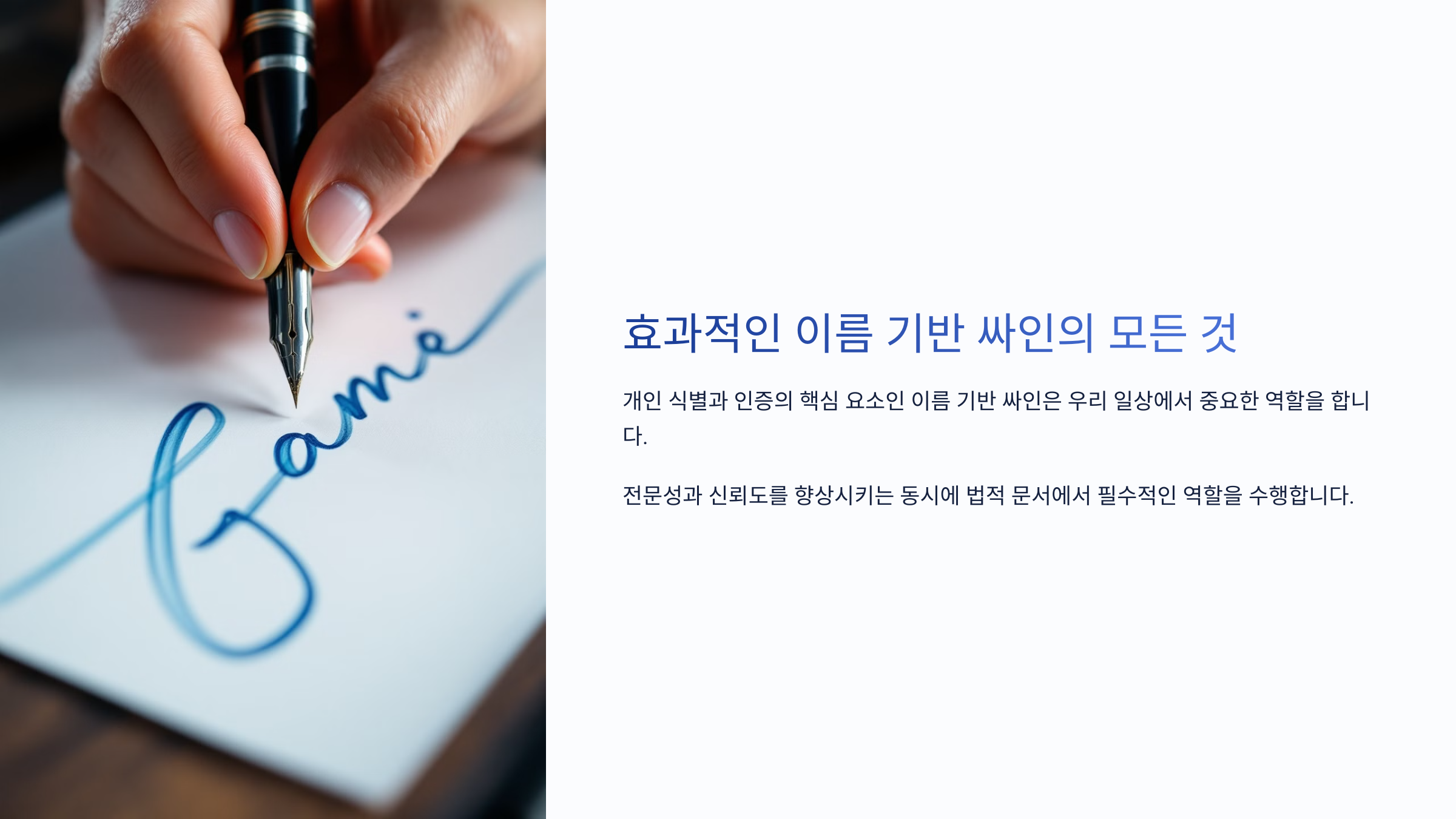
자신의 이름을 활용한 싸인은 가장 기본적이면서도 신뢰감을 주는 스타일이에요. 특히 공식 문서, 계약서, 신용 거래 등에서 본인 확인의 역할을 하기 때문에 더욱 중요하죠. ✅
싸인은 단순한 글씨가 아니라 자신의 브랜드이자 아이덴티티예요. 빌 게이츠, 스티브 잡스, 제프 베이조스처럼 이름을 활용한 싸인을 보면 그들의 개성과 스타일이 명확하게 드러나요.
📌 이름 기반 싸인이 중요한 이유 ✅
이유 설명 공식 문서에서의 신뢰감 이름 기반 싸인은 계약서, 법적 서류에서 본인 확인 수단이 됨 개인 브랜드 강화 고유한 싸인은 나만의 브랜드 이미지와 연결될 수 있음 가독성과 실용성 이름을 기반으로 하면 쉽게 읽히면서도 깔끔한 인상을 줌 위조 방지 효과 독특한 스타일을 더하면 위조가 어려워 보안성이 높아짐 이름을 기반으로 한 싸인은 가독성과 신뢰성을 동시에 확보할 수 있는 강력한 방법이에요. 하지만, 너무 단순하면 흔해 보일 수 있고, 너무 복잡하면 가독성이 떨어질 수 있어요. 그럼 이제, 가독성과 스타일을 적절히 조합하는 방법을 알아볼까요? ✨
가독성과 스타일의 균형 ⚖️
싸인은 가독성이 좋아야 신뢰감을 줄 수 있고, 스타일이 있어야 개성이 살아나요. 하지만 이 두 가지를 동시에 만족시키는 것이 쉽지 않죠. 😵💫너무 복잡한 싸인은 빠르게 작성하기 어렵고, 공식 문서에서 문제가 될 수 있어요. 반대로 너무 단순한 싸인은 개성이 부족해 보일 수 있죠. 그래서 이름을 유지하면서도 멋진 스타일을 가미하는 균형이 중요해요! 🖊️
📌 가독성과 스타일을 조합하는 4가지 원칙 ✅
원칙 설명 1. 핵심 글자는 명확하게 이름의 첫 글자 또는 성을 명확하게 남기고 나머지는 부드럽게 처리 2. 곡선과 직선의 조화 부드러운 곡선과 강한 직선을 조합해 개성 있는 스타일 연출 3. 적절한 속도감 너무 빠르면 흐트러지고, 너무 느리면 부자연스러우니 적절한 속도로 연습 4. 서명의 일관성 싸인의 스타일을 일정하게 유지해 모든 문서에서 동일한 모습 유지 이 원칙을 적용하면 읽기 쉽고, 멋있고, 실용적인 싸인을 만들 수 있어요! 그럼 이제, 이니셜을 활용해 더 특별한 싸인을 만드는 방법을 알아볼까요? ✨
이니셜을 활용하는 방법 🔠
싸인에서 이니셜(첫 글자)을 강조하면 스타일과 개성을 살릴 수 있어요. 특히 긴 이름을 가진 경우, 이니셜을 활용하면 싸인을 짧고 세련되게 만들 수 있죠. ✍️
빌 게이츠(Bill Gates) → B. Gates 일론 머스크(Elon Musk) → E. Musk 이처럼 이니셜을 활용하면 짧으면서도 강한 인상을 주는 싸인을 만들 수 있어요! 🔥
📌 이니셜을 활용하는 4가지 방식 ✅
방식 설명 예시 1. 성 + 이니셜 성을 적고, 이름은 첫 글자만 남기는 방식 "Kim J." / "Choi S." 2. 이니셜 조합 이름과 성의 첫 글자를 합쳐 심플하게 만들기 "J.K." / "S.L." 3. 이니셜 + 서명 스타일 이니셜을 강조하고, 개성 있는 서명 요소 추가 "J.K ✨" / "S.L ↘" 4. 필기체 스타일 이니셜을 손글씨 느낌으로 자연스럽게 연결 "Jk" / "Sl" 이니셜을 활용하면 싸인을 짧고 세련되게 만들 수 있어요! 그럼 이제, 고유한 싸인을 만들기 위한 핵심 요소를 살펴볼까요? 🔥
고유한 싸인 만들기 🌟
싸인은 단순한 서명이 아니라 나만의 개성을 담을 수 있는 요소예요. 비슷한 이름을 가진 사람이 많기 때문에, 독창적인 싸인을 만드는 것이 중요하죠! 🖊️
너무 흔한 싸인은 특별함이 부족해 보일 수 있고, 너무 복잡한 싸인은 빠르게 작성하기 어렵고 실용성이 떨어질 수 있어요. 그래서 간결하면서도 독창적인 요소를 가미하는 것이 핵심! 🔥
📌 고유한 싸인을 만드는 4가지 핵심 요소 ✅
요소 설명 예시 1. 독특한 시작 또는 끝 이니셜이나 이름의 첫 글자에 강한 강조를 주거나, 끝에 독특한 마무리 추가 "J. Kim ↘" / "H. Park ⭐" 2. 필기체 변형 곡선과 직선을 조합해 손글씨 느낌을 자연스럽게 살리기 "Jk" / "P.Song" 3. 특수 기호 활용 별, 밑줄, 점 등을 활용해 독창적인 디자인 추가 "M.Lee ✨" / "S.Lim —" 4. 연속된 흐름 한 획으로 이어지는 부드러운 흐름을 만들기 "JooHyun" / "D.Kim" 이렇게 고유한 요소를 추가하면 나만의 싸인을 완성할 수 있어요! 하지만, 너무 복잡하면 위조 위험이 커질 수 있기 때문에 보안성도 고려해야 해요. 그럼 이제, 싸인의 보안성과 위조 방지 방법을 살펴볼까요? 🔐
보안성과 위조 방지 🔐
싸인은 단순한 스타일이 아니라 법적 효력이 있는 중요한 요소예요. 따라서 위조되기 쉬운 싸인은 큰 문제가 될 수 있죠. 🛑
은행 서류, 계약서, 신용 거래 등에서 싸인을 활용할 때 보안성이 강한 싸인을 사용하는 것이 중요해요. 너무 단순한 싸인은 쉽게 따라 할 수 있으므로, 위조 방지 요소를 추가하는 것이 필요해요! 🔍
📌 위조를 어렵게 만드는 4가지 요소 ✅
요소 설명 예시 1. 복잡한 획 추가 단순한 글씨 대신 독창적인 곡선과 직선을 조합 "J.Lee ↘↗" / "H. Kim ✦" 2. 연속된 필기체 끊어 쓰지 않고 한 번에 이어지는 스타일 "SeoHyun" / "D.Kim" 3. 개성 있는 마무리 특정한 마무리 요소(밑줄, 별, 독창적 형태) 추가 "M.Lee ✨" / "S.Lim —" 4. 필기 속도 조절 너무 빠르거나 느린 싸인은 위조가 쉽기 때문에, 적절한 속도 유지 적절한 균형 유지 보안성이 높은 싸인을 만들면 위조 걱정 없이 안전하게 사용할 수 있어요! 그럼 이제, 이름 싸인 연습법을 알아볼까요? 🖊️
이름 싸인 연습법 🖊️
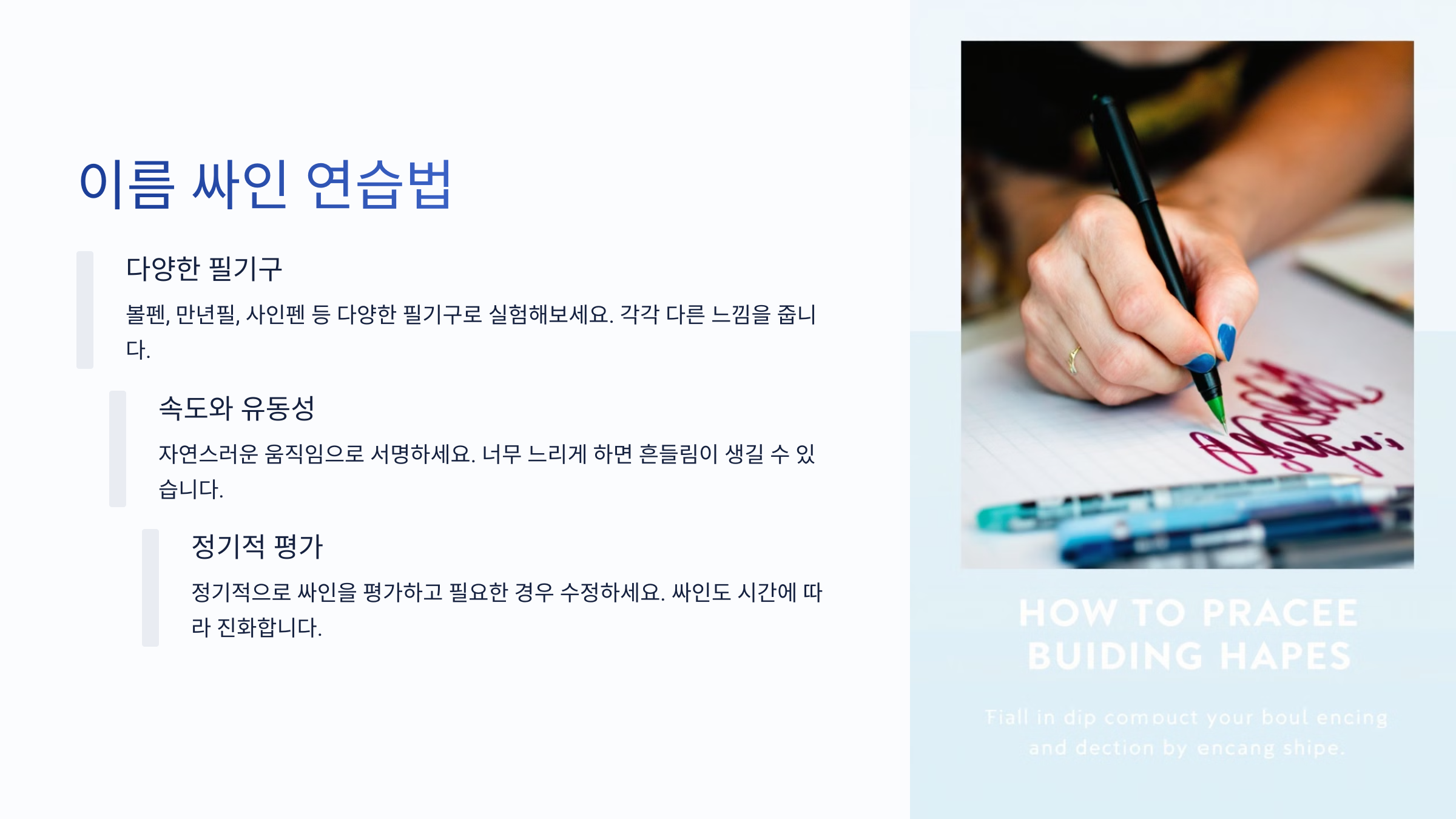
싸인은 손에 익을 때까지 꾸준히 연습하는 것이 중요해요. 처음에는 어색할 수 있지만, 반복 연습을 하면 점점 자연스러워지고 스타일이 완성돼요! ✅
📌 효과적인 이름 싸인 연습법 🔥
연습 방법 설명 1. 기본 형태 연습 이름을 다양한 스타일로 써보면서 자신에게 가장 자연스러운 형태 찾기 2. 반복 연습 한 장에 50~100번씩 반복해서 쓰며 손에 익히기 3. 속도 조절 천천히 쓰면서 완성도를 높인 후 점점 속도를 높여 자연스럽게 만들기 4. 다양한 필기구 활용 볼펜, 만년필, 연필 등 다양한 도구로 연습하여 최적의 도구 찾기 5. 실제 문서 활용 메모, 서류 등에 싸인을 해보면서 실전 감각 익히기 이렇게 연습하면 빠르고 자연스러우면서도 멋진 싸인을 만들 수 있어요! 마지막으로, 이름 싸인과 관련된 자주 묻는 질문(FAQ)을 정리해 볼게요. 📢
FAQ
Q1. 이름 싸인을 만들 때 가장 중요한 요소는?
A1. 가독성과 개성을 동시에 고려해야 해요. 너무 단순하면 흔해 보이고, 너무 복잡하면 실용성이 떨어질 수 있어요. ✍️
Q2. 싸인을 빠르게 연습하는 방법이 있나요?
A2. 천천히 연습한 후 점점 속도를 올리는 방식이 좋아요. 또한, 같은 스타일을 반복 연습하면 손에 익숙해져요. 🖊️
Q3. 싸인을 자주 바꿔도 되나요?
A3. 비공식적인 싸인은 변경 가능하지만, 공식적인 문서에서 사용하는 싸인은 일관성을 유지하는 것이 좋아요. 📄
Q4. 싸인을 멋있게 보이게 하는 팁이 있나요?
A4. 이니셜을 강조하거나, 곡선과 직선을 조합해 개성을 살리는 것이 좋아요. 특히, 마무리 스타일(밑줄, 점, 별 등)을 추가하면 더욱 멋져 보여요! ✨
Q5. 싸인을 연습할 때 실수를 줄이는 방법은?
A5. 연필이나 디지털 도구로 초기에 연습하는 것이 좋아요. 완성된 스타일이 정해지면 볼펜이나 만년필로 연습하는 것이 효과적이에요. ✅
Q6. 유명인의 싸인을 참고해도 되나요?
A6. 네! 빌 게이츠, 스티브 잡스, 일론 머스크 등 유명인의 싸인을 참고하면 어떤 요소를 활용해야 하는지 배울 수 있어요. 하지만 그대로 따라 하기보다는 자신만의 개성을 추가하는 것이 중요해요. 🏆
Q7. 싸인을 꾸준히 연습하려면 어떻게 해야 하나요?
A7. 하루 5분씩 짧게라도 꾸준히 연습하는 것이 효과적이에요. 또한, 싸인을 녹화하거나 다양한 필기구로 연습하면 스타일을 더 빨리 확립할 수 있어요. 🚀
Q8. 디지털 싸인과 손글씨 싸인은 어떤 차이가 있나요?
A8. 디지털 싸인은 태블릿이나 스마트폰에서 생성한 전자 서명이며, 손글씨 싸인은 종이에 직접 작성하는 아날로그 방식이에요. 공식적인 문서에서는 전자 서명이 점점 더 많이 활용되고 있어요. 📱